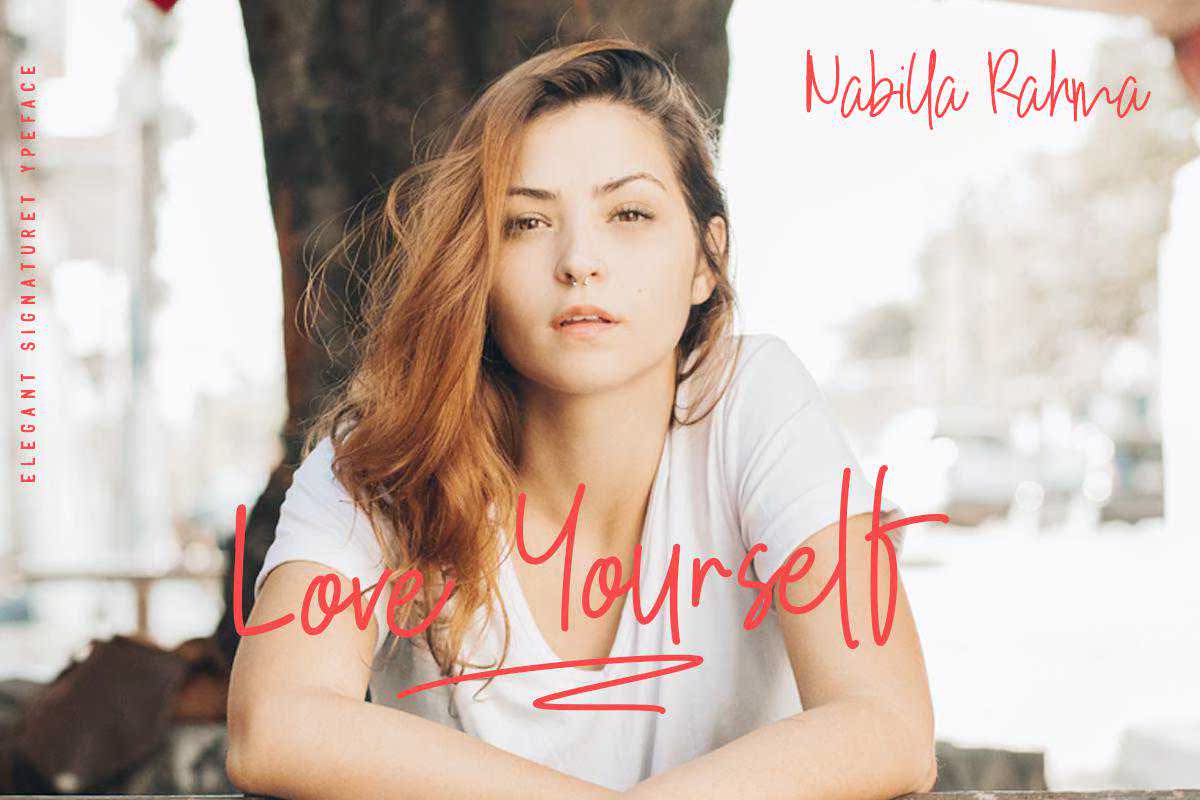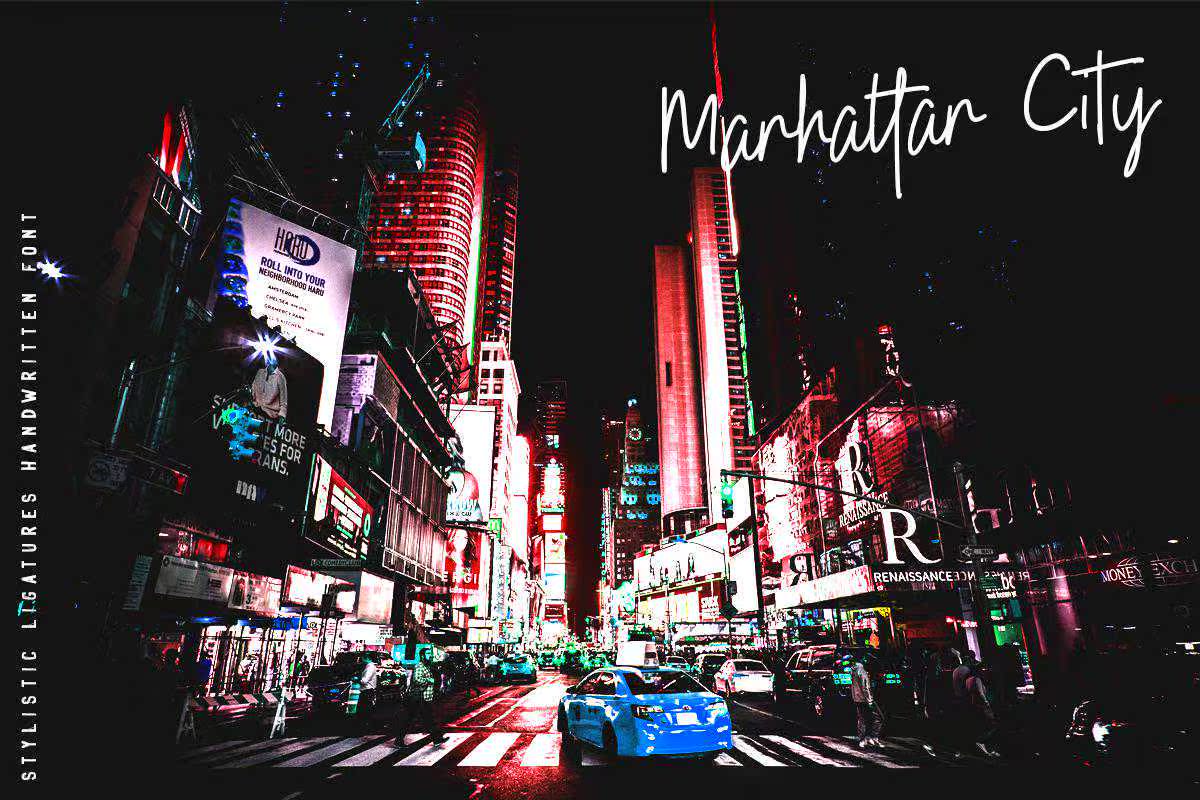
介绍风格字体为Kinderspiel的新产品。使用手写和签名说明的字体,并使用粗略版本的流行语。Kinderspiel非常适合创建字体和图形设计项目,如:邀请、卡片、服装、明信片、赠品卡、标识、书皮、,等等,介绍具有风格字体的全新Kindspeel.AtyFace,手写和签名说明,以及具有粗略版本的时尚设计。Kindspeel非常适合创建字体设计和平面设计项目,如邀请、卡片、服装、明信片、赠品卡、标识、书皮等